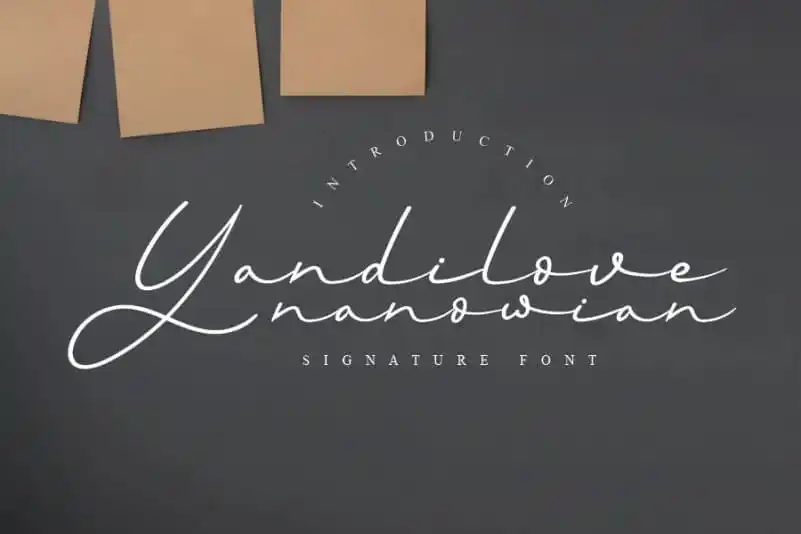
Yandilove Handwritten Font – Download Grátis
A Yandilove Handwritten Font é uma elegante escolha para quem busca uma escrita fluida e descontraída. Ideal tanto para projetos formais quanto informais, este tipo imediatamente se destaca por sua versatilidade, sendo perfeitamente adaptável a diversos estilos de design. Suas linhas suaves e harmoniosas criam um contraponto acolhedor aos elementos mais elaborados das criações gráficas. Perfeita para designers que buscam uma transição natural entre o formal e o informal, esta fonte é uma ótima opção para aqueles que desejam dar um toque único a seus projetos. Com Yandilove Handwritten Font, você pode criar layouts não só atraentes, mas também muito envolventes, mantendo ao mesmo tempo aquela delicadeza e elegância que caracteriza uma escrita imprimida a mão.